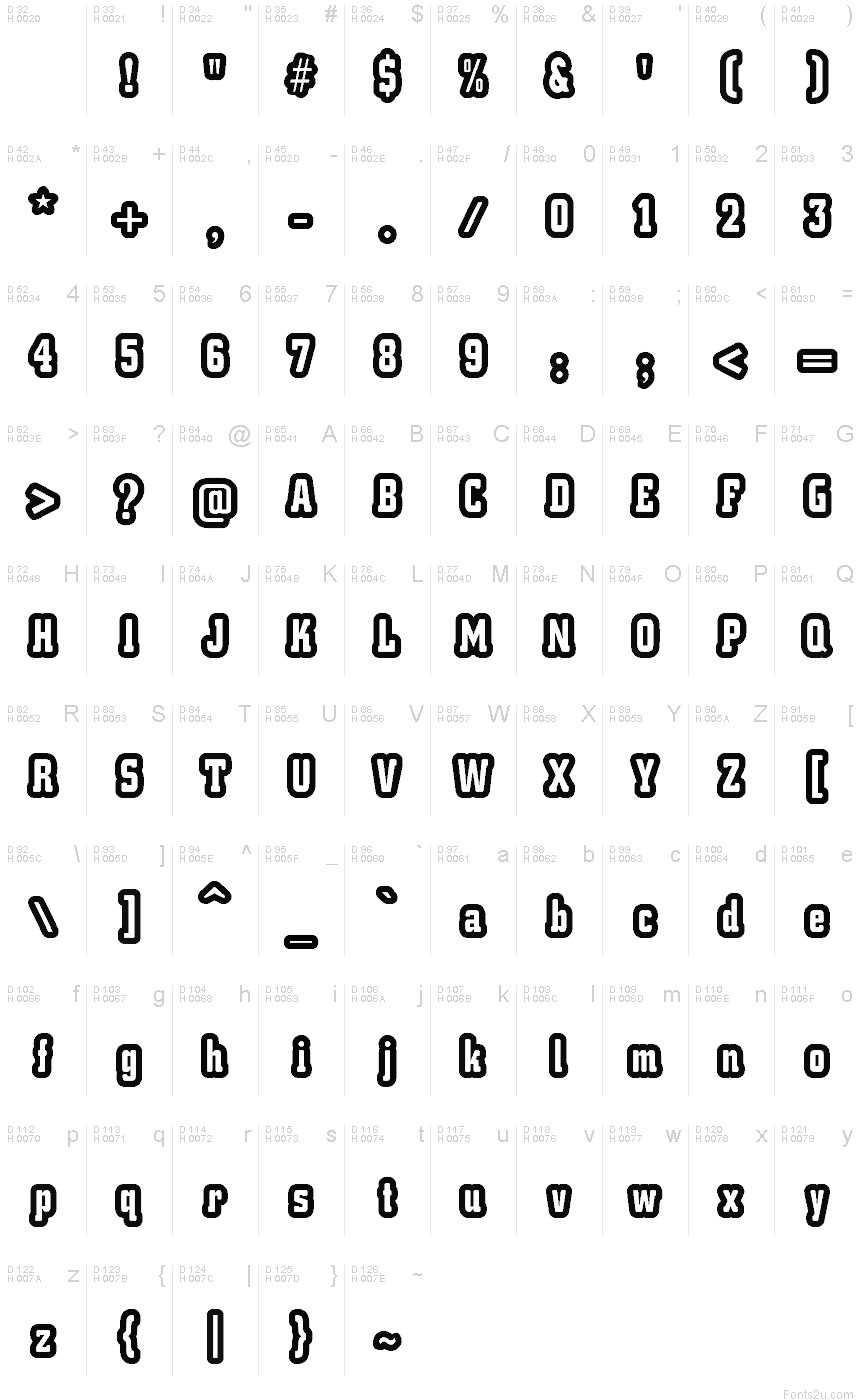
d-LaCruz
Tipografa condensada semi-serif con una grueso borde.
Condensed semi-serif typeface with big outline.
d La Cruz es una tipografía de gruesa outline homenaje por la vuelta al comienzo, al principio, a la mitad del todo a la calle de La Cruz en Ampuero -Cantabria- donde vivo ahora, crecí y nací.